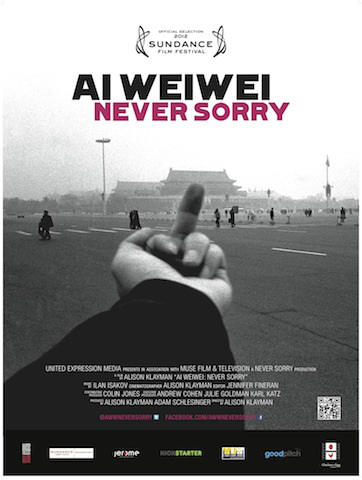
Typo von Ai WeiWei - Never Sorry
sieht für mich nach der hier aus:
es gibt auch eine kostenlose version (Lietz Lindau Hamburg) bei dafont.
und der designer der lietz lindham, hannes siengalewicz, bestätigt hier und hier, dass es seine schriftart ist, die verwendet wurde. allerdings zeigt ein blick auf eine höher aufgelöste version des schriftzugs, dass sie dafür die unebenheiten der schrift etwas aufgeräumt haben.